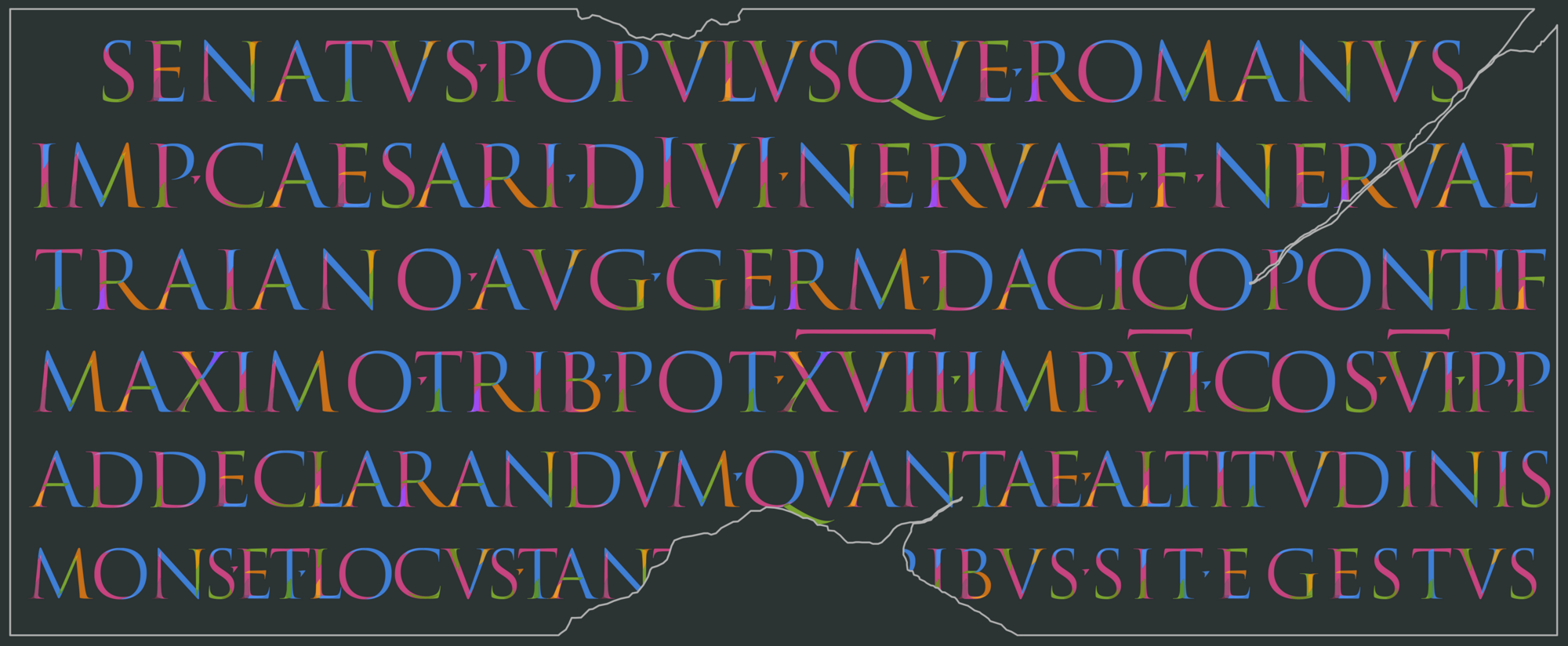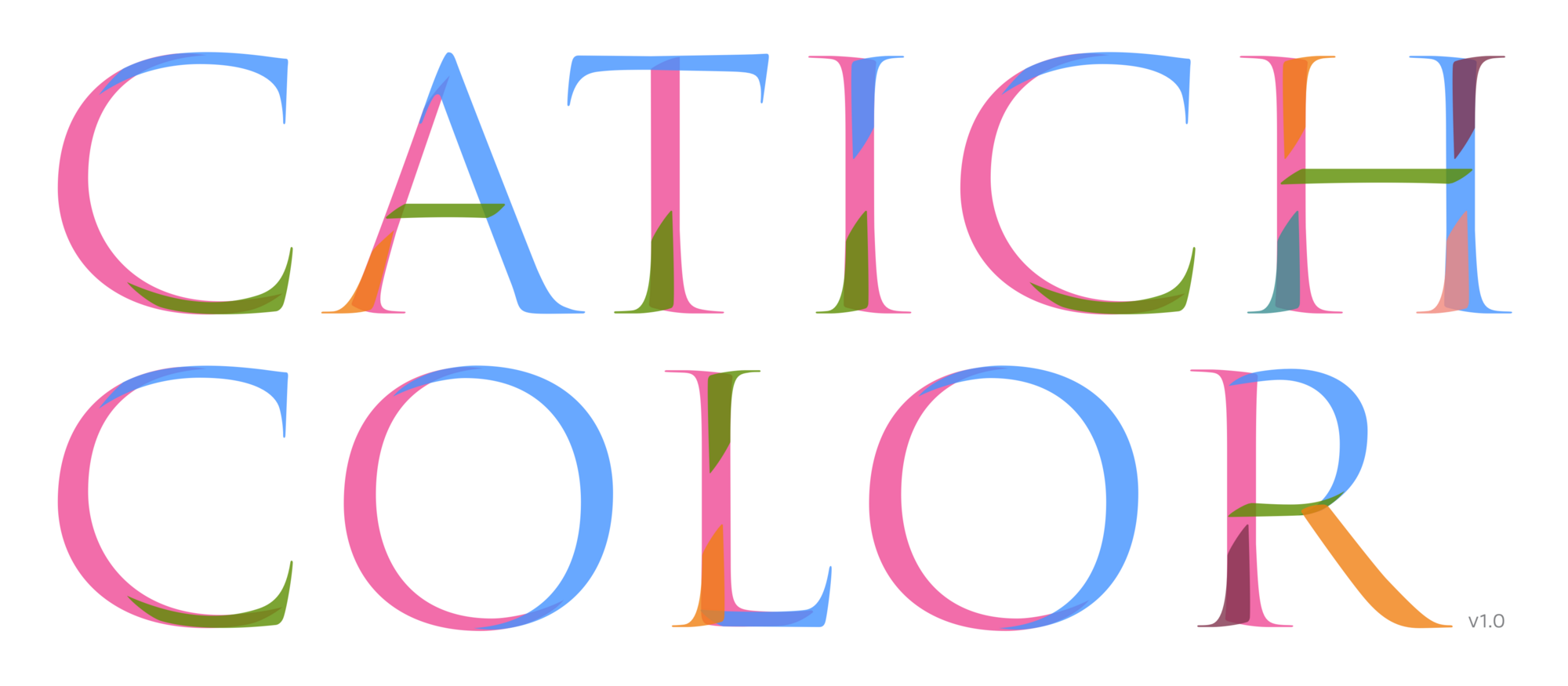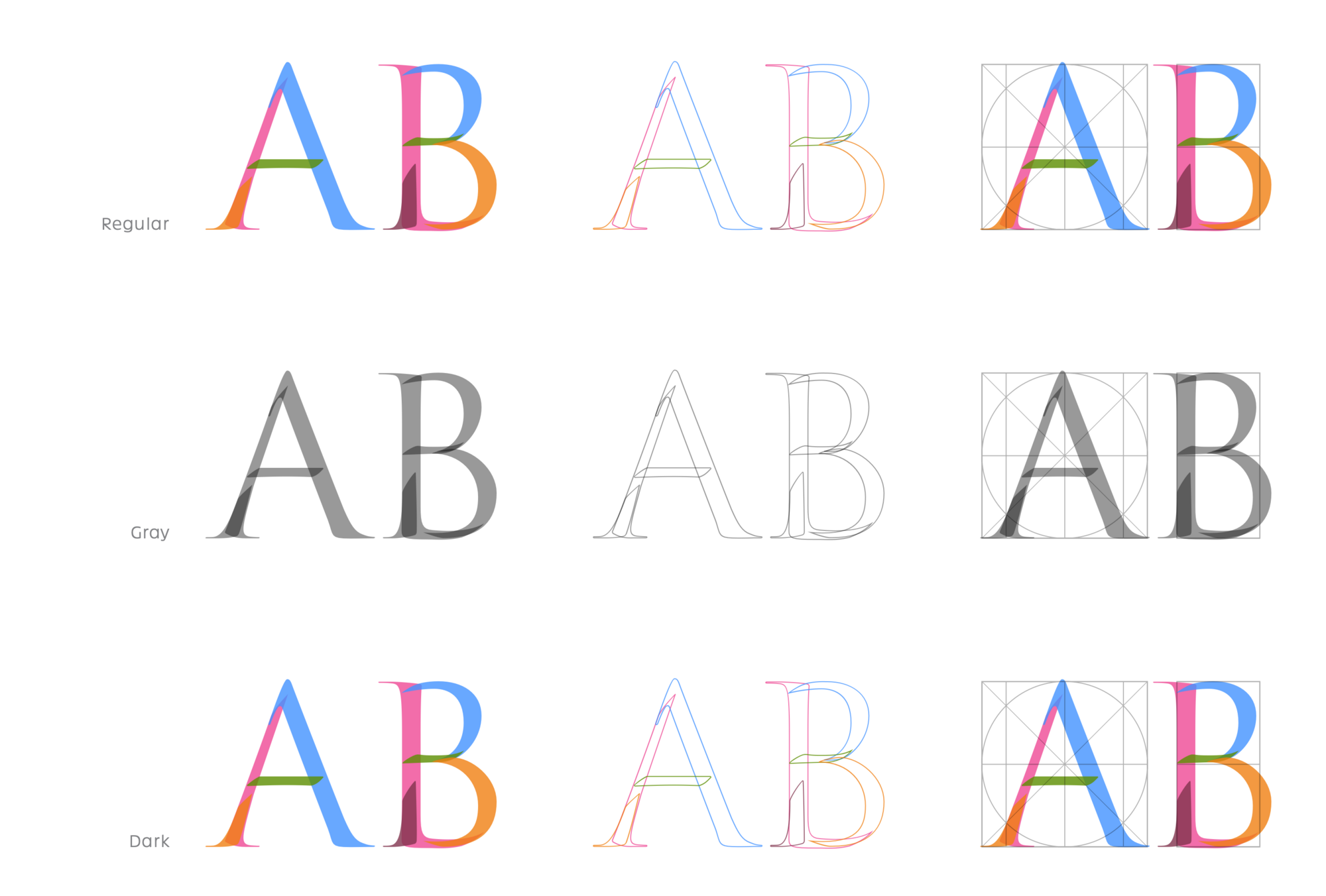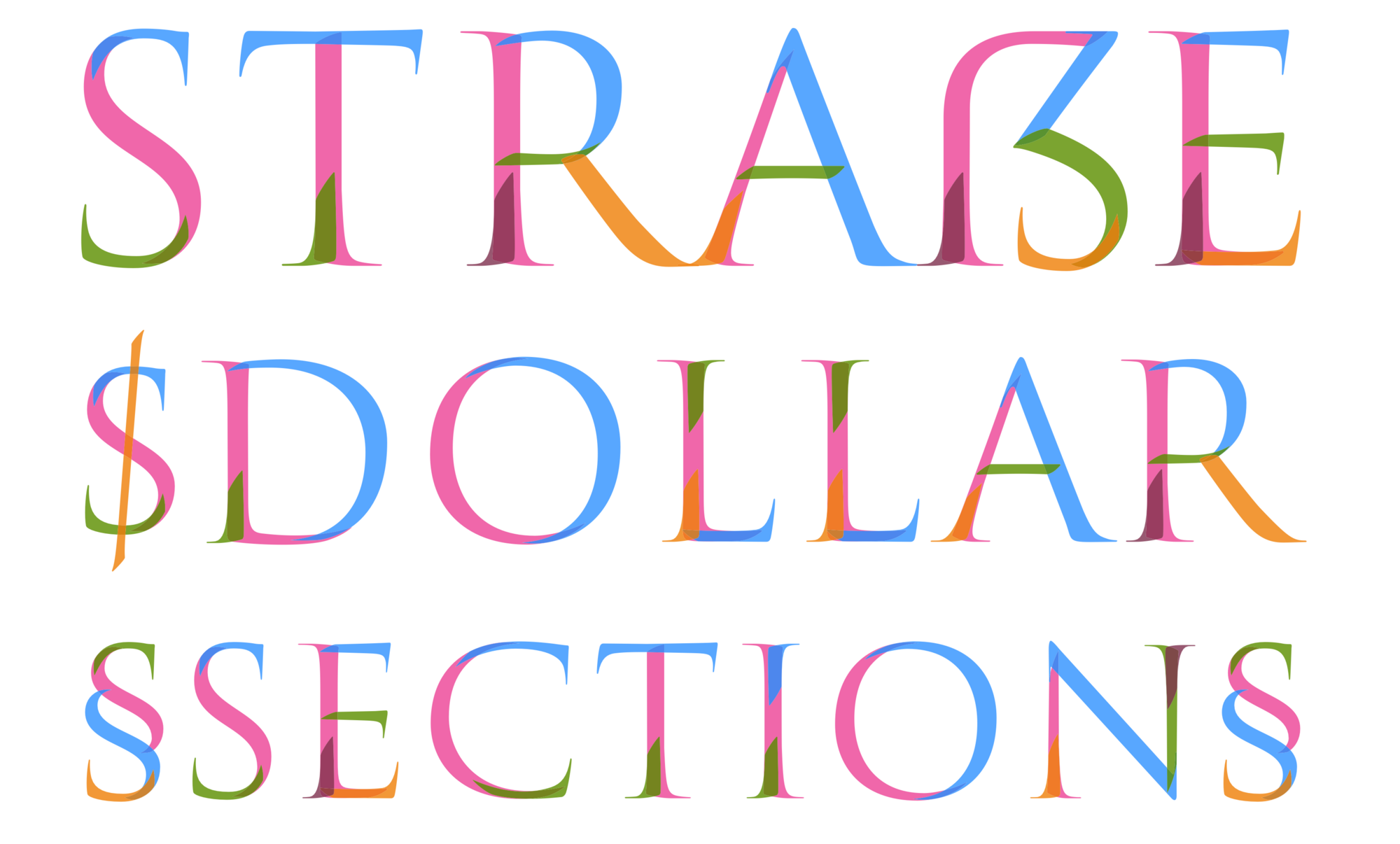
Die Catich Color ist eine Umsetzung der Schreibvorlagen von Edward Catich, der in seinem Buch »The Origin of the Serif« die Entstehung der römischen Capitalis-Schriften aus der Schreibung mit dem Pinsel ableitete. Diese Schreibvorlagen wurden in farbige Schriften in mehreren Varianten überführt, die die die einzelnen Schreibzüge zeigen: Es gibt drei Grundschnitte: farbig, Graustufen und gefüllt. Per OpenType umschaltbar sind für alle drei Varianten eine Umriss-Darstellung und ein Raster im Hintergrund.